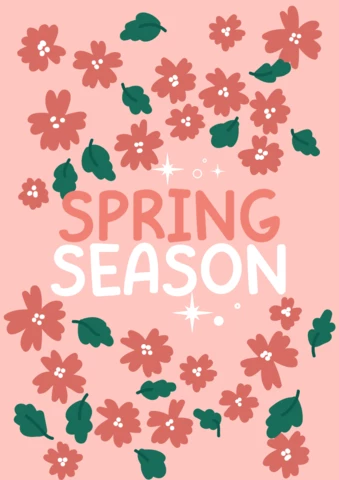
Modèle de design d'affiche pour le printemps avec des fleurs décoratives, des feuilles vertes et une typographie ludique.
Éditer dans Design Studio Télécharger en JPGÉlevez vos projets de printemps avec notre modèle de design floral vibrant, présentant une typographie ludique et des marguerites et pivoines décoratives—parfait pour des cartes de vœux, des affiches ou des décorations inspirées de la nature !